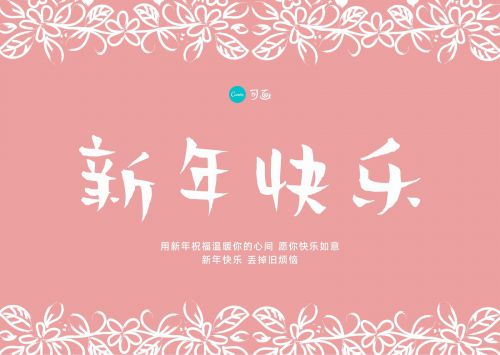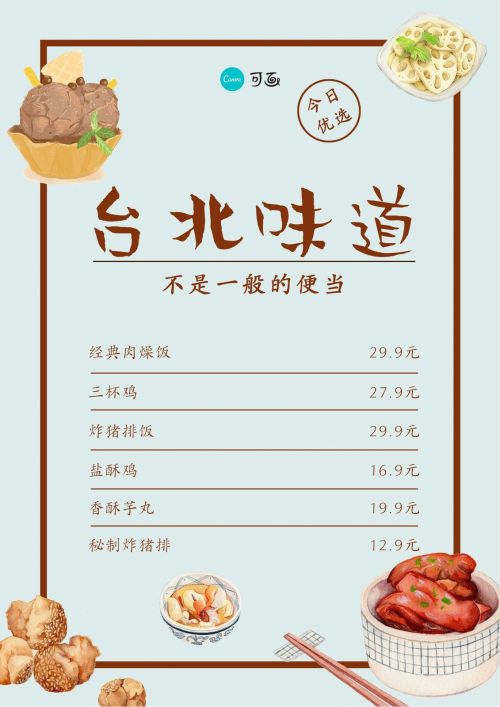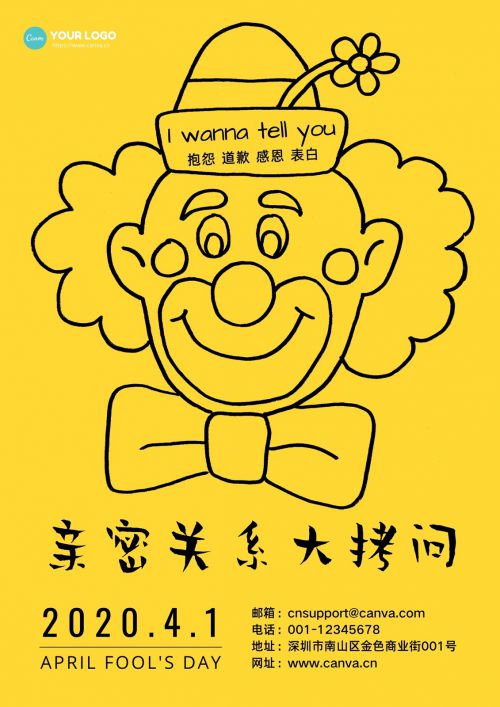
贤二体
【贤二体】是一款兼具中国风与手写质感的简体中文手写体,支持免费商用授权。作为手写体家族中的特色字体,贤二体以方正字形为基础,融合传统书法韵味与现代设计美学,形成独特的视觉风格。 贤二体字形方正稳重,重心居中平衡,中宫宽博的结构设计增强了字体的包容性与可读性。笔型采用圆润处理,粗重均匀的线条配合圆头笔画,既保留手写书法的自然韵味,又通过笔画断开的设计避免连笔带来的杂乱感,展现出刚柔并济的视觉张力。 贤二体适合应用于书法作品复刻、文化宣传海报、传统节日设计等场景,其方正中带着圆润的独特字形,能有效提升视觉亲和力。作为免费商用字体,它兼顾艺术性与实用性,为中文设计项目提供兼具传统韵味与现代审美的手写字体选择。